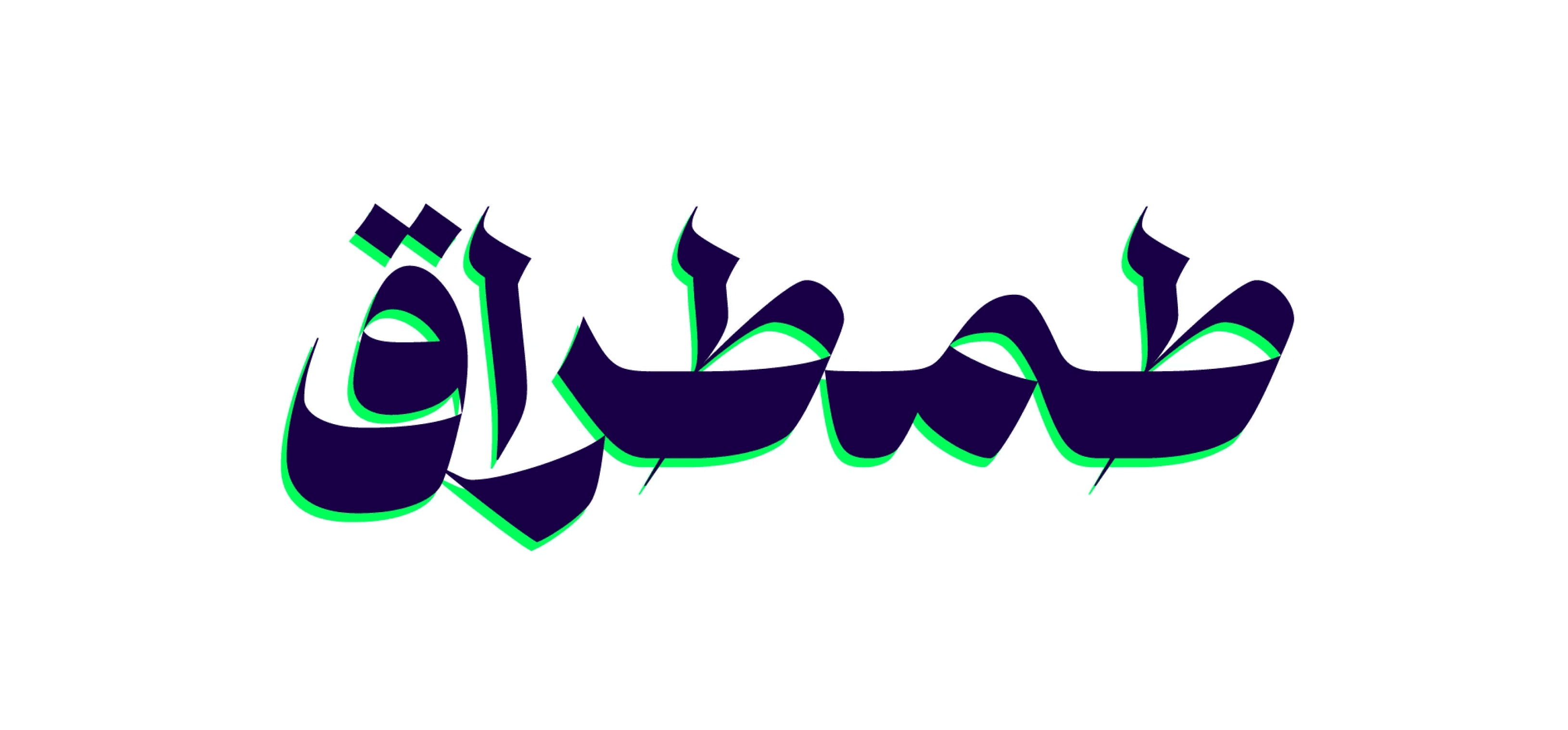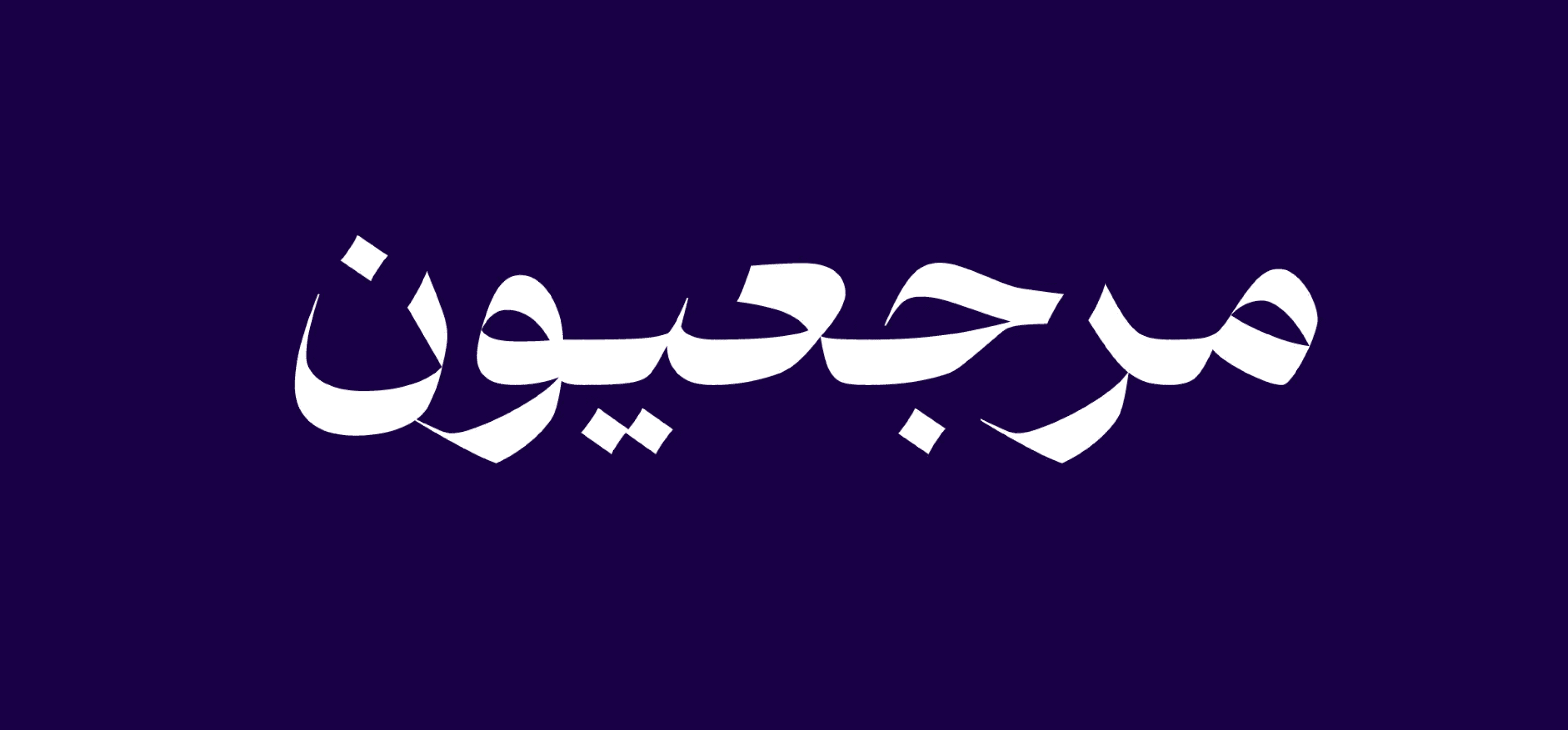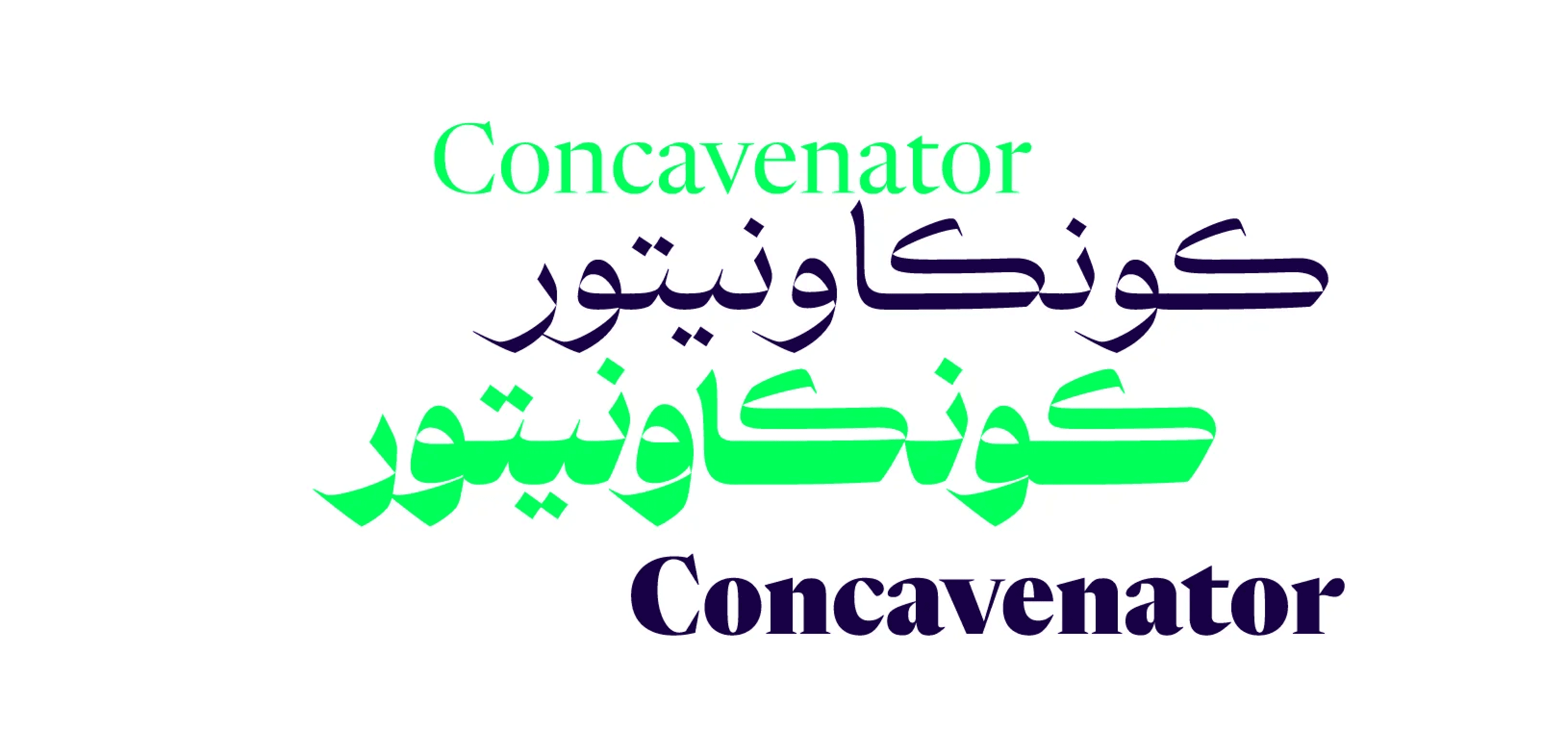
خط پیکان متأثر بوضوح من خط النسخ، ويتميّز بجُرأته وطابعه الجاد.
من أبرز سماته التغيّرات المفاجئة في اتجاهات الحروف، والتباين الحاد جدًا في سماكة الخطوط، مما يجعله فريدًا ومختلفًا بشكل لافت. هيكله مليء بالخطوط المستقيمة، وجسمه يتكوّن من حواف حادّة وقاطعة، كأنّه يحمل طابعًا هجوميًا بصريًا.
ينصح باستخدامه بحذر، وقد يُقال مازحًا: "يرجى إبعاد خط پیکان عن متناول الأطفال!"